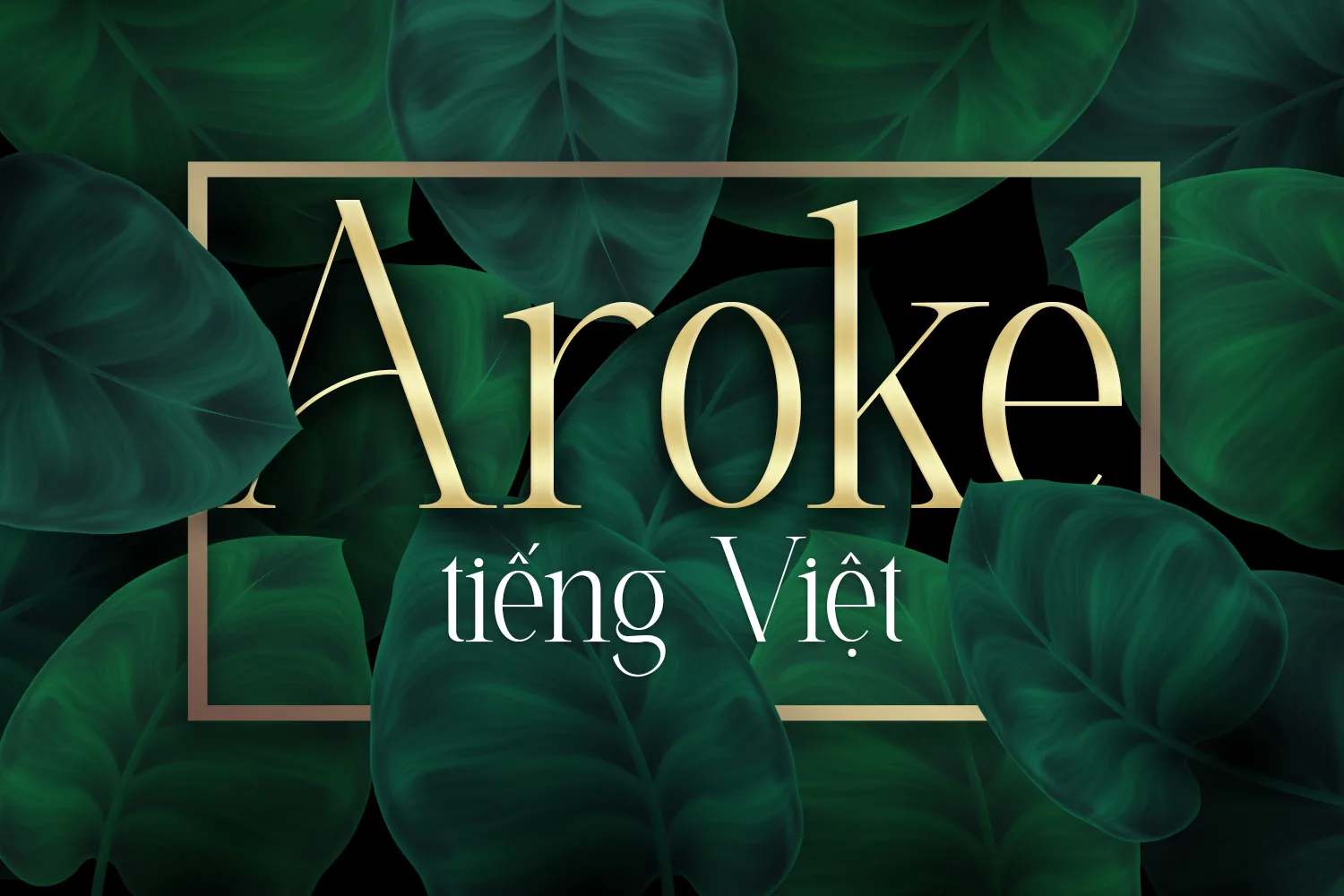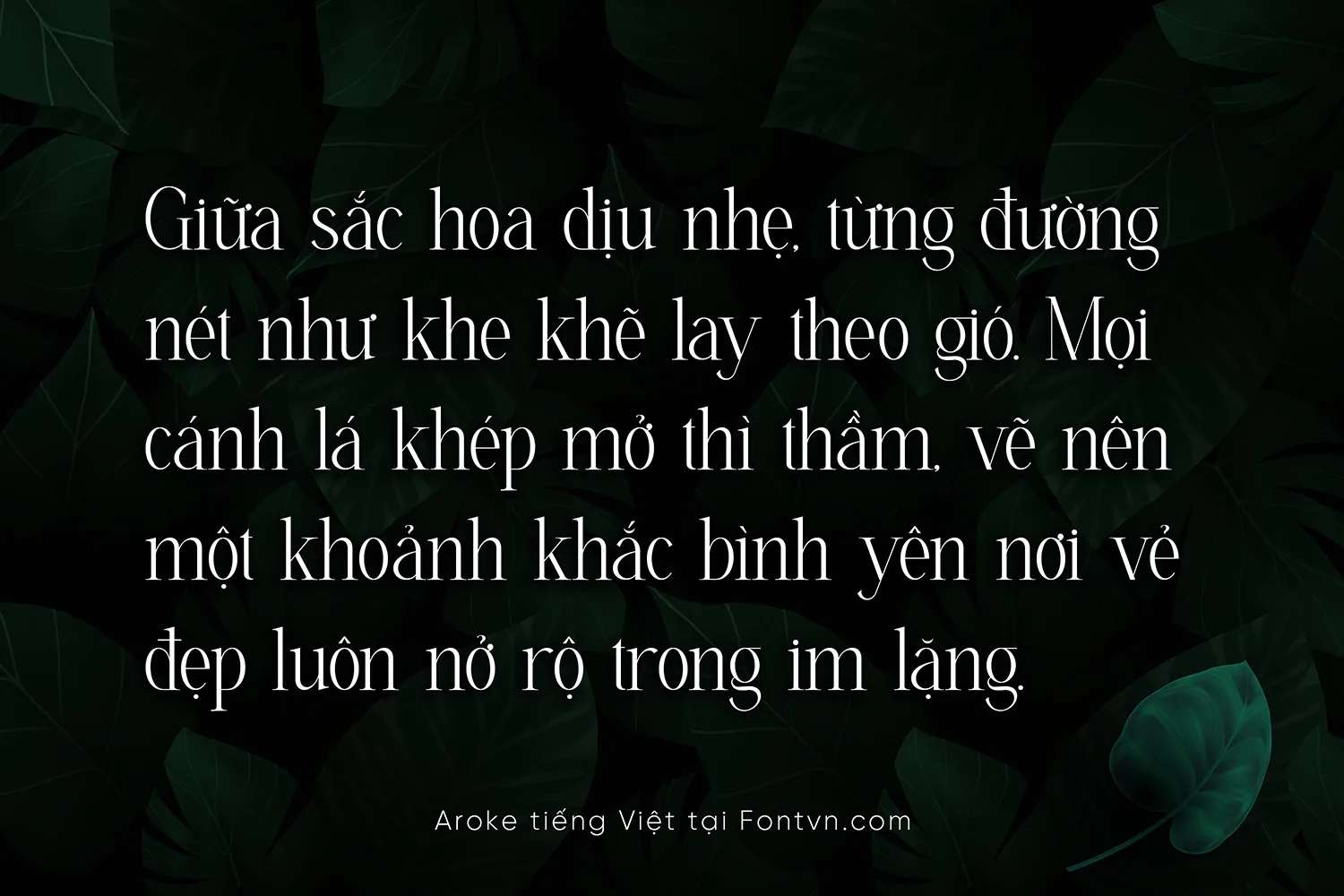
DVN Aroke tiếng Việt – Font chữ thanh mãnh và quyến rũ
DVN Aroke là một kiểu chữ serif mang phong thái thanh mãnh, quyến rũ và hiện đại, được thiết kế dành riêng cho những dự án cần sự tinh tế và sang trọng. Với dáng chữ cao, đường nét mảnh mai kết hợp những đường cong nhẹ nhàng, DVN Aroke tạo nên cảm giác thời trang – editorial – cao cấp ngay từ cái nhìn đầu tiên.
Font đặc biệt phù hợp trong các thiết kế như:
– Poster thời trang
– Bộ nhận diện thương hiệu cao cấp
– Tiêu đề editorial, tạp chí
– Bao bì mỹ phẩm, nước hoa
– Social content mang tone sang – tinh tế
DVN Aroke hỗ trợ đầy đủ tiếng Việt, đảm bảo trải nghiệm thị giác hài hòa, mượt mà ở mọi kích thước chữ.
Nếu bạn đang tìm một font serif vừa mềm mại, vừa có sự dứt khoát thời thượng, DVN Aroke sẽ là lựa chọn hoàn hảo để nâng tầm thiết kế của bạn.